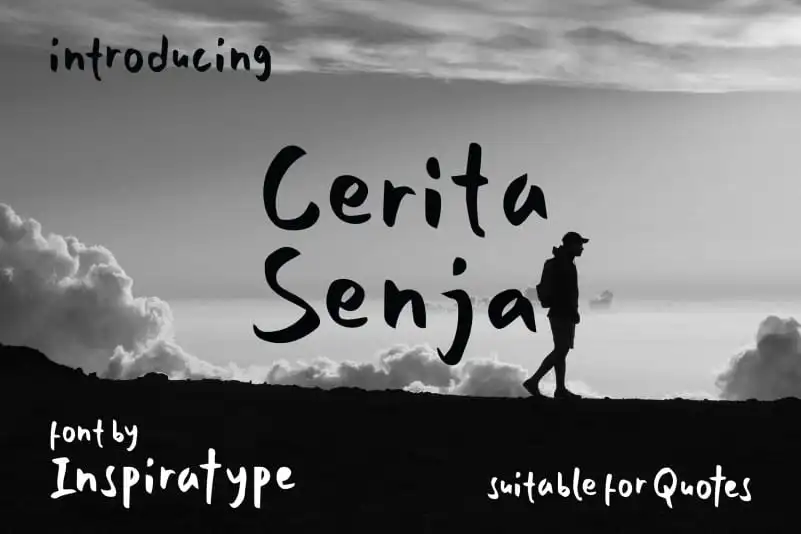
Cerita Senja – Quotes Font – Download Grátis
A fonte ‘Cerita Senja Quotes’ foi criada com cuidado e paixão por um designer chamado inspirasign. Ela se destaca no mundo das fuentes display, feita à mão para imitar clássicos cartazes. Esta font é uma maravilha para quem deseja personalizar os designs de logotipos, etiquetas, assinaturas de carta, arte impressa e muito mais. Além da versão em letras maiúsculas e minúsculas com números e sinais de pontuação, a ‘Cerita Senja Quotes’ oferece uma ampla gama de variações para cada caractere. Inclui alternativas do OpenType, ligaturas comuns e até mesmo swashes para que você possa personalizar seus designs conforme desejar. Esta font é perfeitamente adequada para criar um design único em qualquer aplicação visual.
Designer: inspirasign